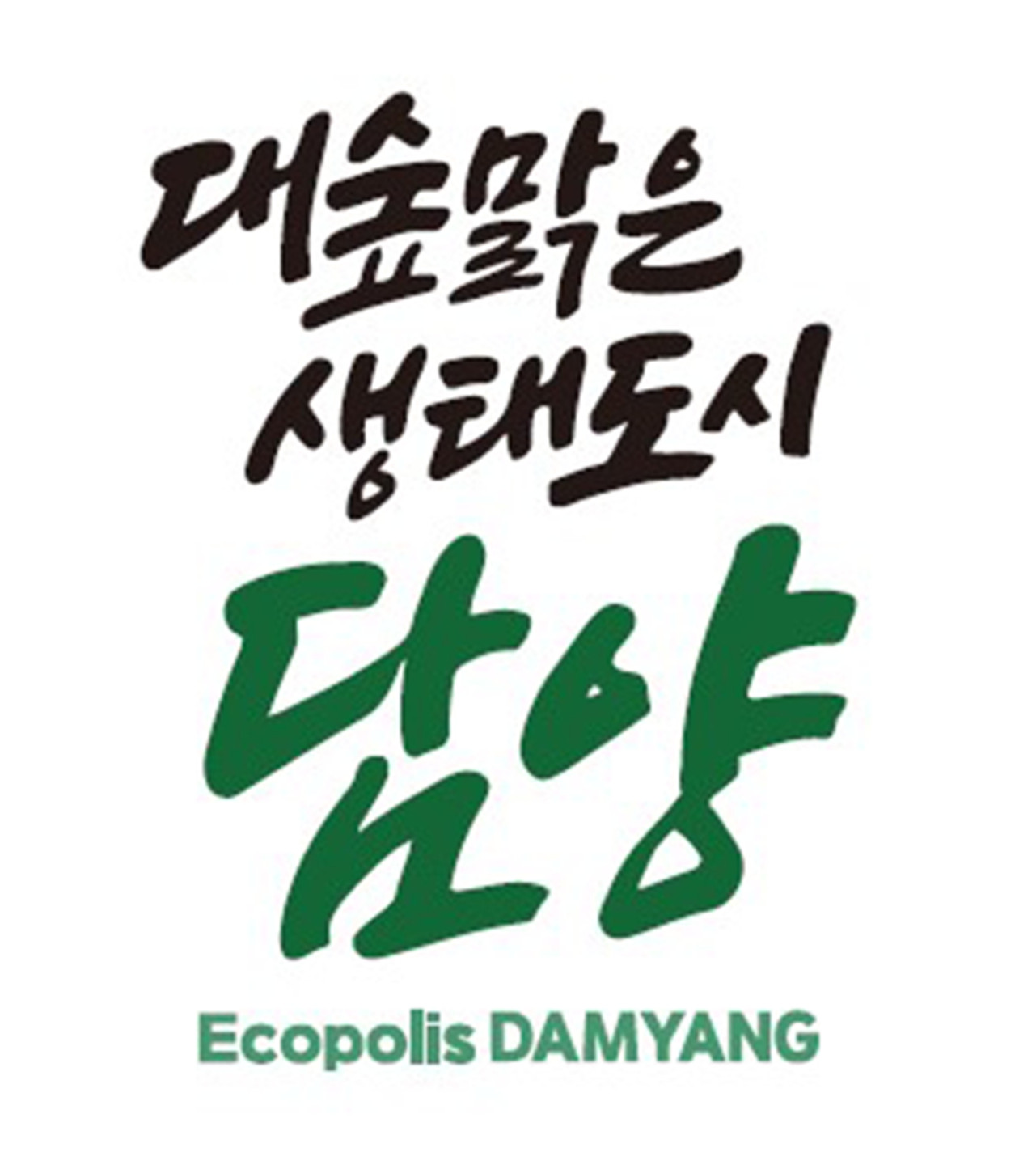
담양 슬로건 Ecopolis DAMYANG 폰트 제발뭔가요 폰트만 여러개 덧대보면서 찾는데 맞는게 안 보입니다 똑같은 폰트로 하라는데 폰트를 모른대서 찾아서 하는 중인데 눈만 죽겠습니다 대충 특징이 안쪽으로 들어가는 c / 짧은 p / 꺾임 없는 l / 꺾임 없이 둥글게 이어지는 G정도인데 되게 두껍기까지합니다